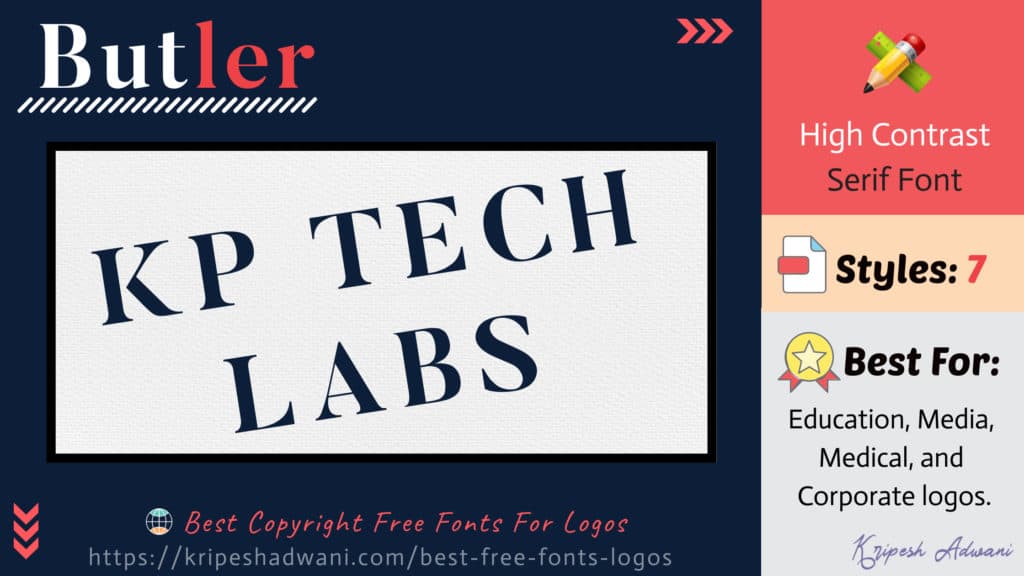
로고를 위한 23가지 최고의 무료 글꼴(2022) – 디자이너를 위한 저작권 무료 글꼴
게시 됨: 2022-08-27글꼴은 로고 디자인 프로젝트에서 없어서는 안될 부분입니다 . 그래픽 디자이너는 모든 글꼴이 고유한 개성을 가지고 있으며 올바른 글꼴이 브랜드에 놀라운 효과를 줄 수 있다는 데 동의할 것입니다!
그러나 브랜드 테마에 맞는 무료 글꼴을 선택하는 것은 어려울 수 있습니다!
이 문제를 해결하기 위해 수백 개의 저작권이 없는 글꼴 을 연구하고 시도했습니다. 이 기사와 함께 나왔습니다 .
로고 및 디자인을 위한 23가지 최고의 무료 글꼴
1. 앵커 잭
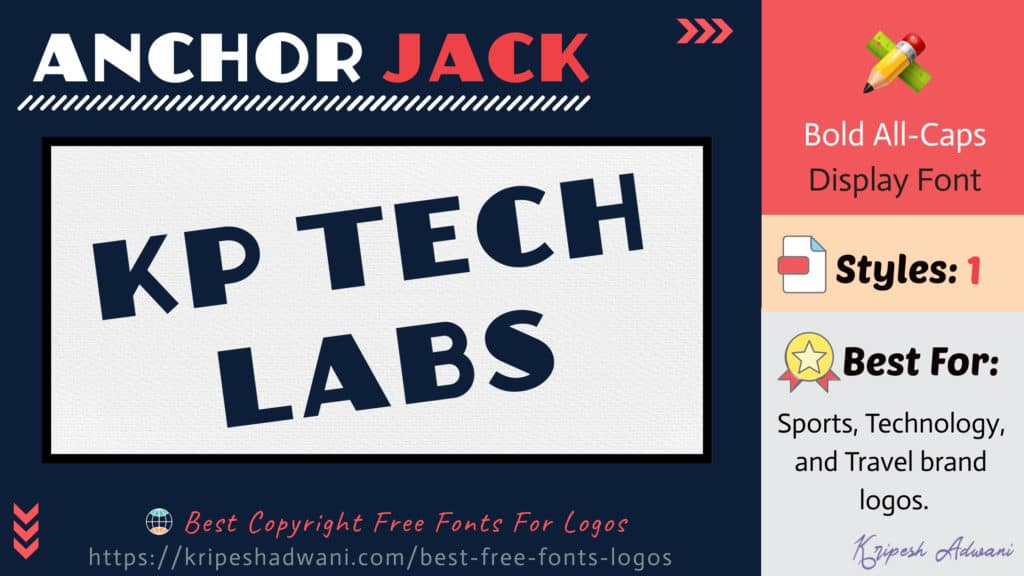
Anchor Jack은 Art Deco에서 영감을 받은 대담한 전체 대문자 디스플레이 글꼴 입니다. 이 글꼴은 스포츠, 기술 및 여행 브랜드 로고와 정말 잘 어울립니다.
- 디자이너 : AJ Paglia
2. 오비트론
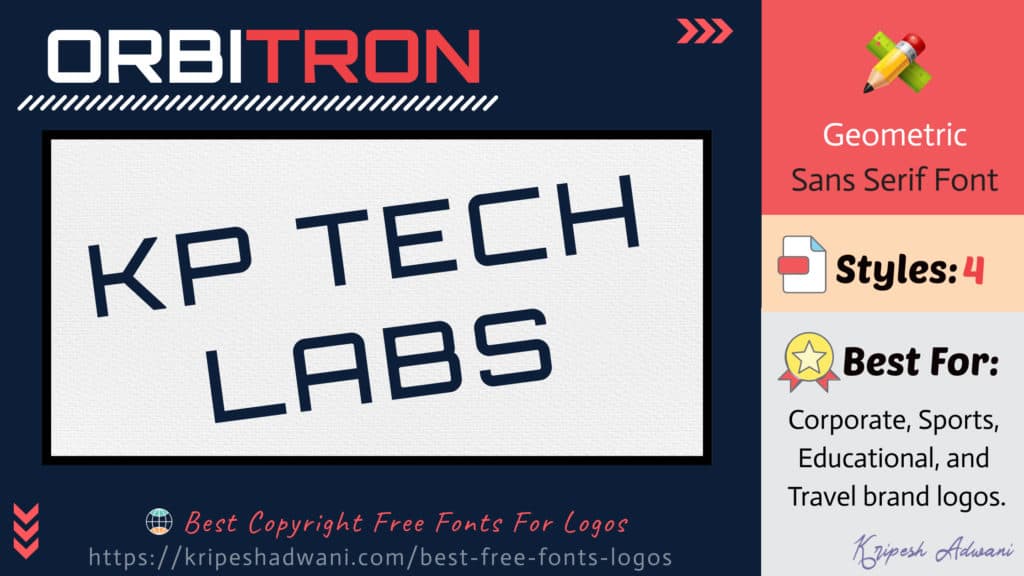
Orbitron은 미래적인 분위기가 가미된 기하학적인 Sans Serif 글꼴입니다! 라이트, 미디엄, 볼드, 블랙 등 4가지 무게로 출시되었습니다!
이 글꼴은 기업, 교육, 스포츠 및 여행 브랜드 로고에 탁월한 선택입니다.
- 디자이너 : 마리사 파소스
3. 모하우
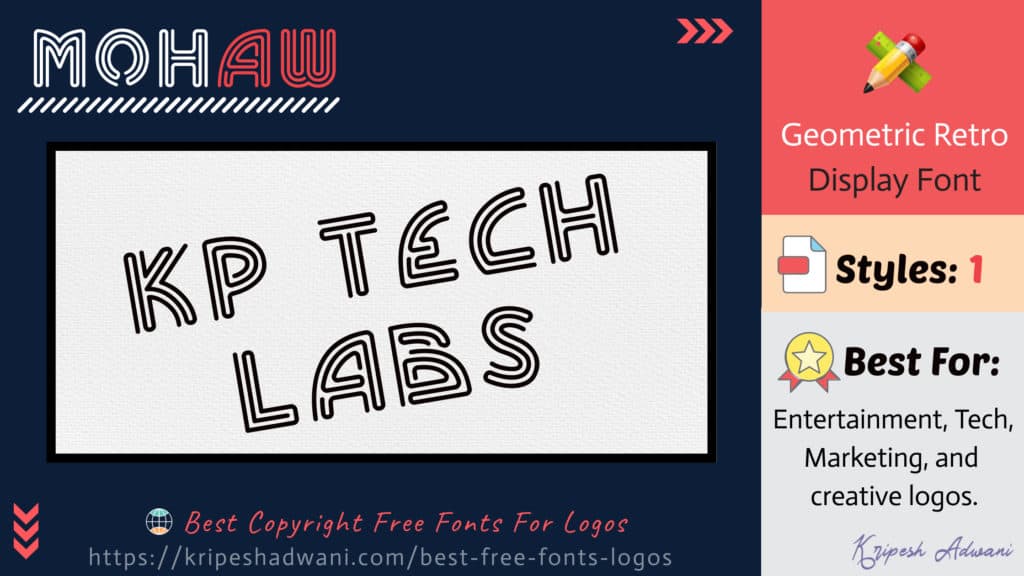
Mohaw는 네온 스타일에서 영감을 받은 부드럽고 흐르는 직선이 있는 기하학적 복고풍 디스플레이 글꼴입니다. 매우 세련된 글꼴이며 엔터테인먼트, 기술, 마케팅 및 이와 유사한 크리에이티브 로고에 적합한 옵션이 될 수 있습니다.
- 디자이너 : 사카토미 디자인
4. 자야바루
Jaya Baru는 장난기 많고 재미있는 Sans Serif 글꼴입니다. 부드러운 곡선은 거의 만화 같은 느낌을 줍니다. 이 글꼴은 엔터테인먼트, 예술, 어린이 및 식품 브랜드 로고와 정말 잘 어울립니다!
- 디자이너 : 샤프 리잘
5. 트라이베카
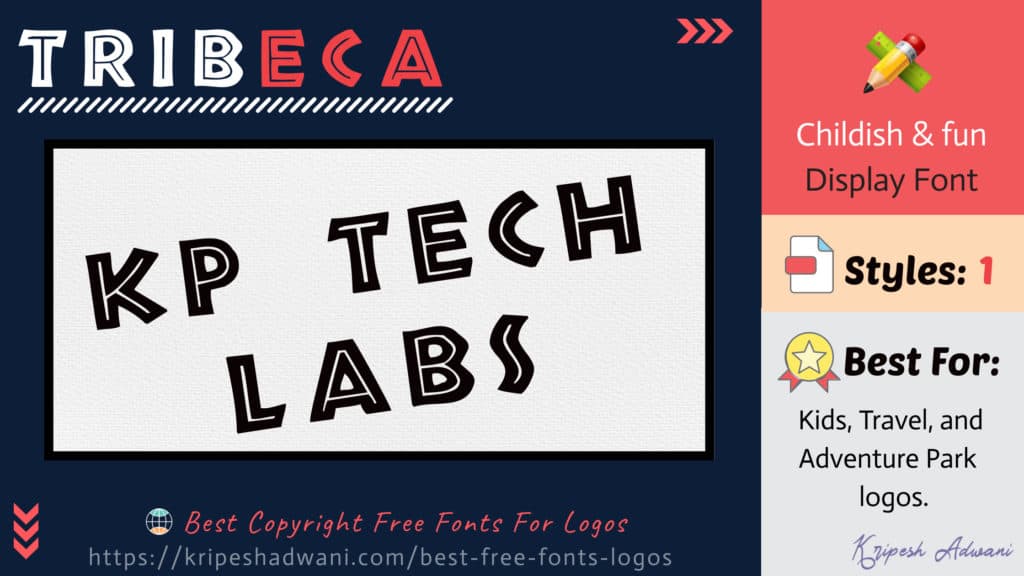
Tribeca는 유치하고 재미있는 디스플레이 글꼴입니다. 대담한 흰색 윤곽선이 있어 강하고 자신감 있는 분위기를 줍니다. Kids, Travel, Adventure Park 로고 에 사용할 수 있습니다.
- 디자이너 : 언블라스트
6. 폭풍 돌풍
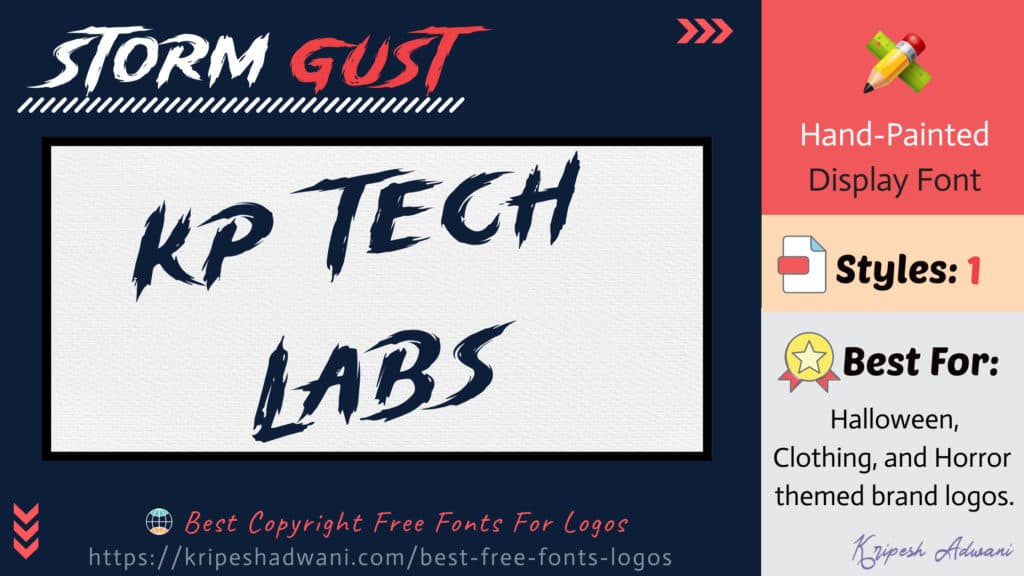
Storm gust는 공포 테마의 손으로 그린 디스플레이 글꼴입니다. 거친 획이 대담하고 무서운 인상을 줍니다. 이 글꼴은 할로윈, 의류 및 공포 테마 브랜드 로고에 적합합니다.
- 디자이너 : 한젤스페이스
7. 아이소메트레토스
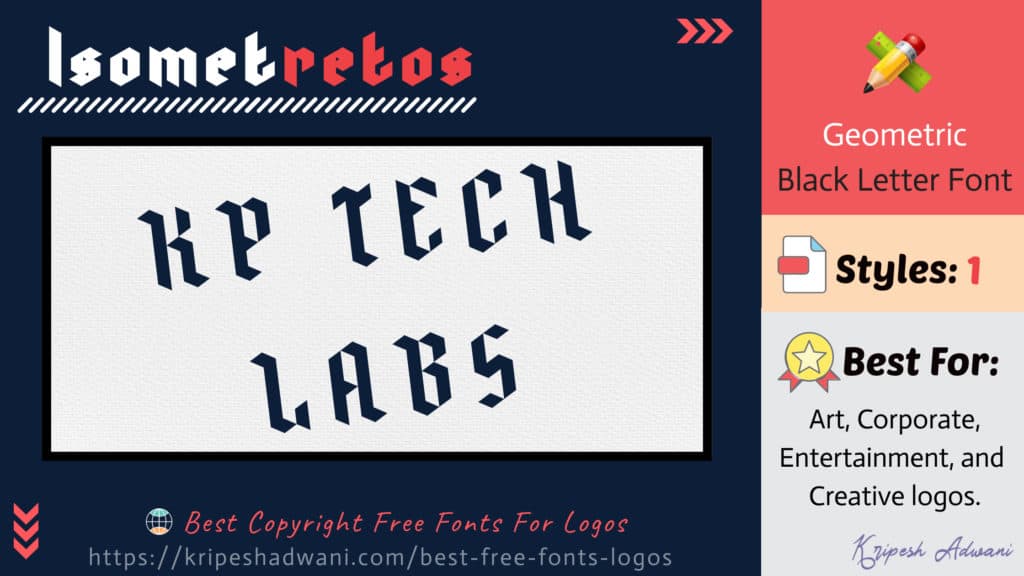
Isometretos는 격자에 삼각형으로 구성된 기하학적 검정 문자 글꼴입니다. 상당히 미니멀하고 고급 스러워 보이며 대문자와 소문자로 구성되어 있습니다.
Art, Corporate, Entertainment, Creative 로고에 사용할 수 있습니다.
- 디자이너 : 벤자민 블라홀츠
8. 큐리
Curely는 손으로 쓴 스타일의 멋진 전체 대문자 스크립트 글꼴입니다. 소녀스러운 느낌이 강한 폰트로 Arts, Kids, Fashion 브랜드 로고에 가장 잘 어울리는 폰트입니다.
- 디자이너 : 콘스탄틴 스튜디오
9. 가장 운이 좋은 사람
Luciest Guy는 친근한 매력이 있는 대담한 Sans Serif 글꼴입니다. 엔터테인먼트, 교육, 뉴스, 음식 및 예술 로고에 이상적입니다.
- 디자이너 : 난시
10. 바닐라
바닐라는 부드럽고 물결 모양의 글자가 있는 귀엽고 유치한 디스플레이 글꼴입니다. 그것은 아이들과 관련된 장난기 있고 평온한 분위기를 자아냅니다.
이 글꼴은 Kids, Arts, Entertainment, Clothing 브랜드 로고에 가장 적합합니다.
- 디자이너 : 큐티 익스플로전
11. 캡사이신
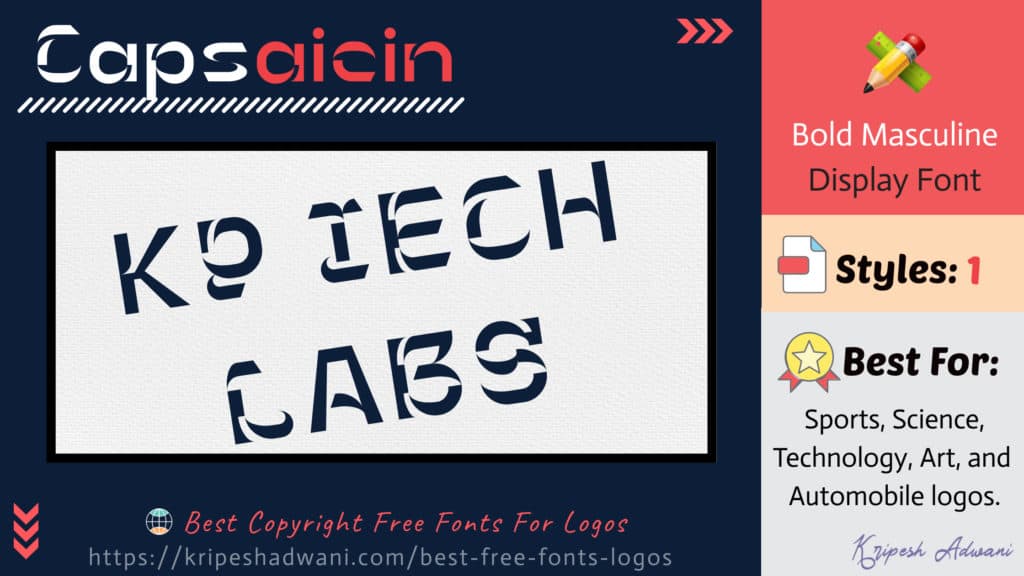
캡사이신은 피부에 작열감을 유발하는 고추에 존재하는 물질입니다. 이 글꼴은 날카로운 모서리와 거친 모양으로 동일한 글꼴을 현대적으로 적용한 것입니다! 스포츠, 과학, 기술, 예술 및 자동차 로고에 이상적입니다.
- 디자이너 : 마이클 싱
12. 문자열
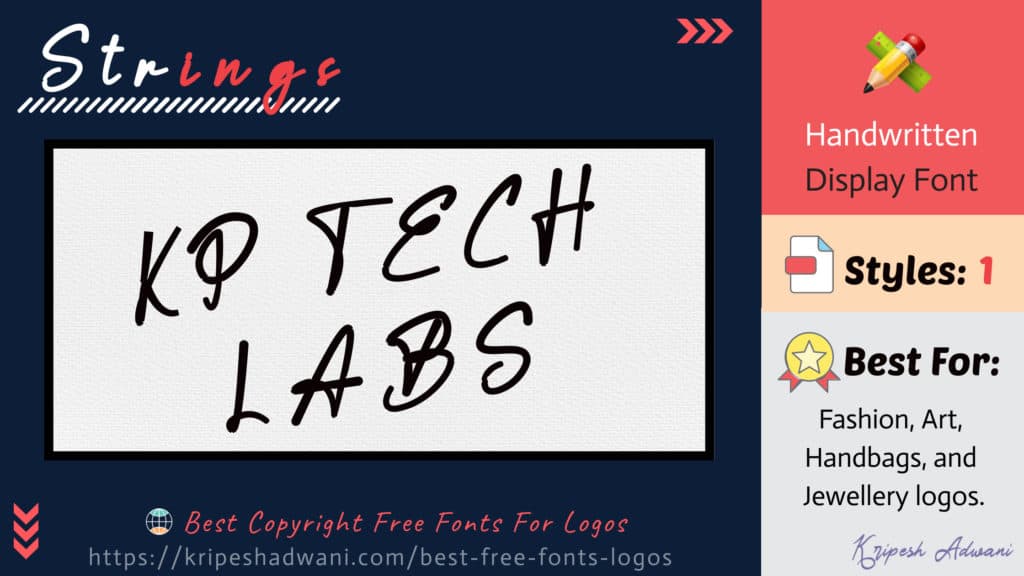
Color Tube는 부드럽고 매끄러운 곡선이 있는 아름다운 필기체 글꼴입니다. 이 글꼴은 패션, 아트, 핸드백, 보석 브랜드 로고에 가장 적합합니다.
- 디자이너 : 레즈 프로덕션
13. 비트시프트
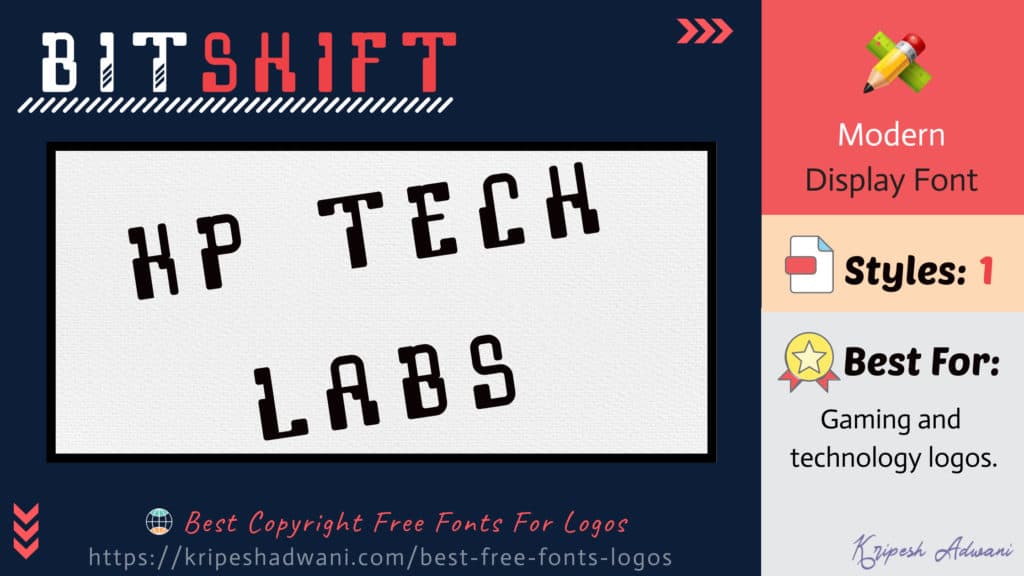
Bitshift는 게임을 중심으로 하는 디스플레이 카테고리의 무료 글꼴입니다. 이 글꼴은 게임 및 기술 로고에 가장 적합합니다.
- 디자이너 : 테렌스 커런